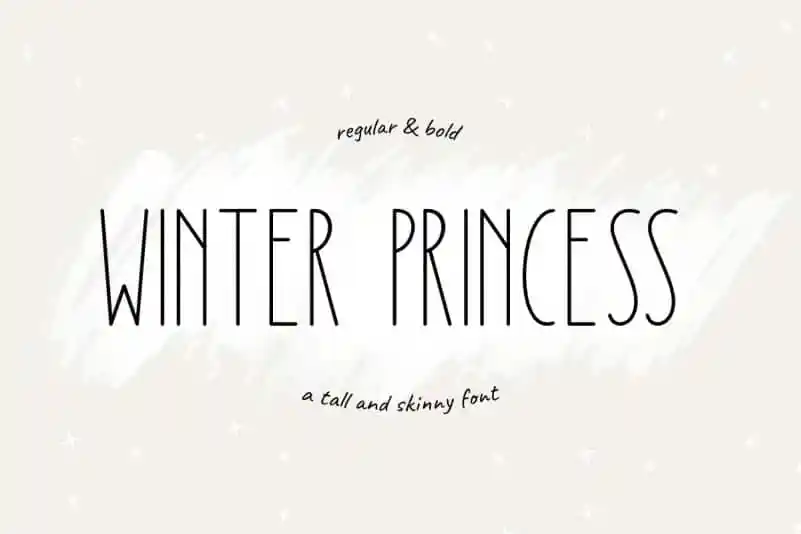
Winter Princess Sans Serif Font Demo – Download Grátis
A fonte Winter Princess Sans Serif é uma escolha perfeita para quem procura um tipo sans serif que ofereça alta expressividade sem perder elegância. Com letras altas e finas, ela se destaca como uma fonte fácil de ler ideal para qualquer aplicação visual. Este tipo pode ser facilmente adaptado tanto em estilo regular quanto bold, o que faz da Winter Princess Sans Serif uma opção versátil para várias aplicações digitais. Seja para adicionar um toque criativo a frases de autor, personalizar camisetas infantis ou criar design de marcas, essa fonte atinge perfeitamente seus objetivos. Com seu formato sinuoso e elegante, Winter Princess Sans Serif se destaca em projetos como SVG, criação de marca, trabalhos para impressão (como mugs), além de projetos de cut com fio (Cricut). Ela pode ser facilmente incorporada nas suas criações, dando um toque único e moderno a qualquer design.
Designer: jimtypestudio